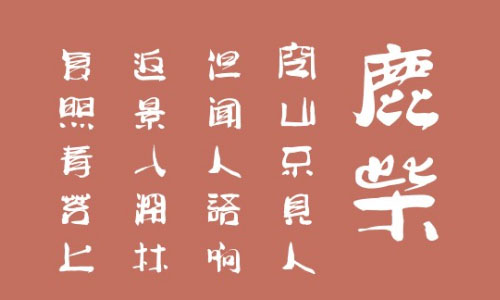
南構(gòu)周洋字體是一款非常不錯的隸書字體,由書法家周洋先生創(chuàng)作,該字體筆畫粗壯有力,字形大方得體,整體效果出色,能夠應(yīng)用于文本裝潢、信息展示、網(wǎng)頁設(shè)計、篆刻制模、數(shù)據(jù)制作、裝潢設(shè)計、計算藝術(shù)設(shè)計、視覺設(shè)計、字帖等一切合法應(yīng)用場景,歡迎有需要的朋友前來下載。